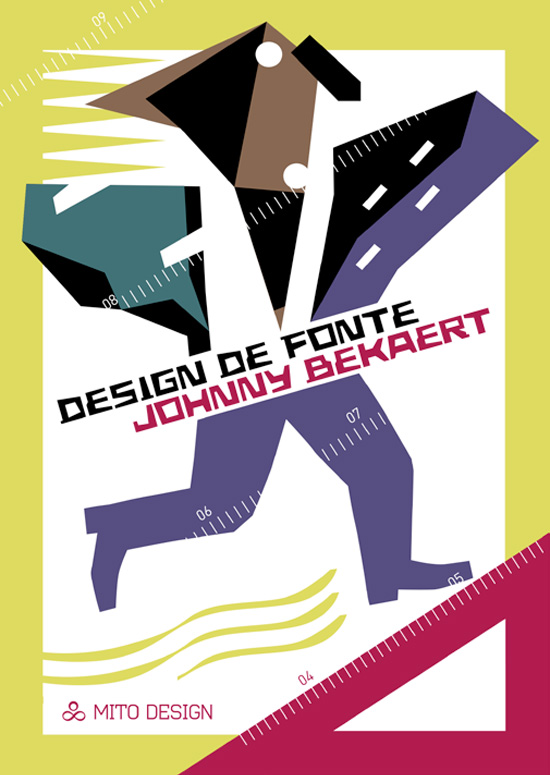
Het resultaat van 40 jaar passie voor grafisch design.
Het verhaal over de 30 lettertypes die ik heb ontworpen, met toepassingen op affiches, logo’s, boekencovers, en meer.
Voorwoorden van Ben Bos (The Netherlands), Arnaud Huftier (France), Michel Michiels (Belgium), Prof. dr. Luc Devroye (Canada), Pedro Guitton (Brazil)
«Bekaert beheerst de kunst van beknoptheid van communicatie op een zeer Belgische manier, waarbij hij zijn opdrachten verwoordt in eenvoudige posters, korte teksten of slogans en zorgvuldig vervaardigde letterontwerpen. Zijn oeuvre doet denken van de tekenstijl van Hergé, en de satire die vele Vlaamse vertellers kenmerkt. Gebrek aan respect voor autoriteit - een handelsmerk van de meeste sociale denkers - kleurt zijn werk.» Prof. Dr. Luc Devroye, Canada.